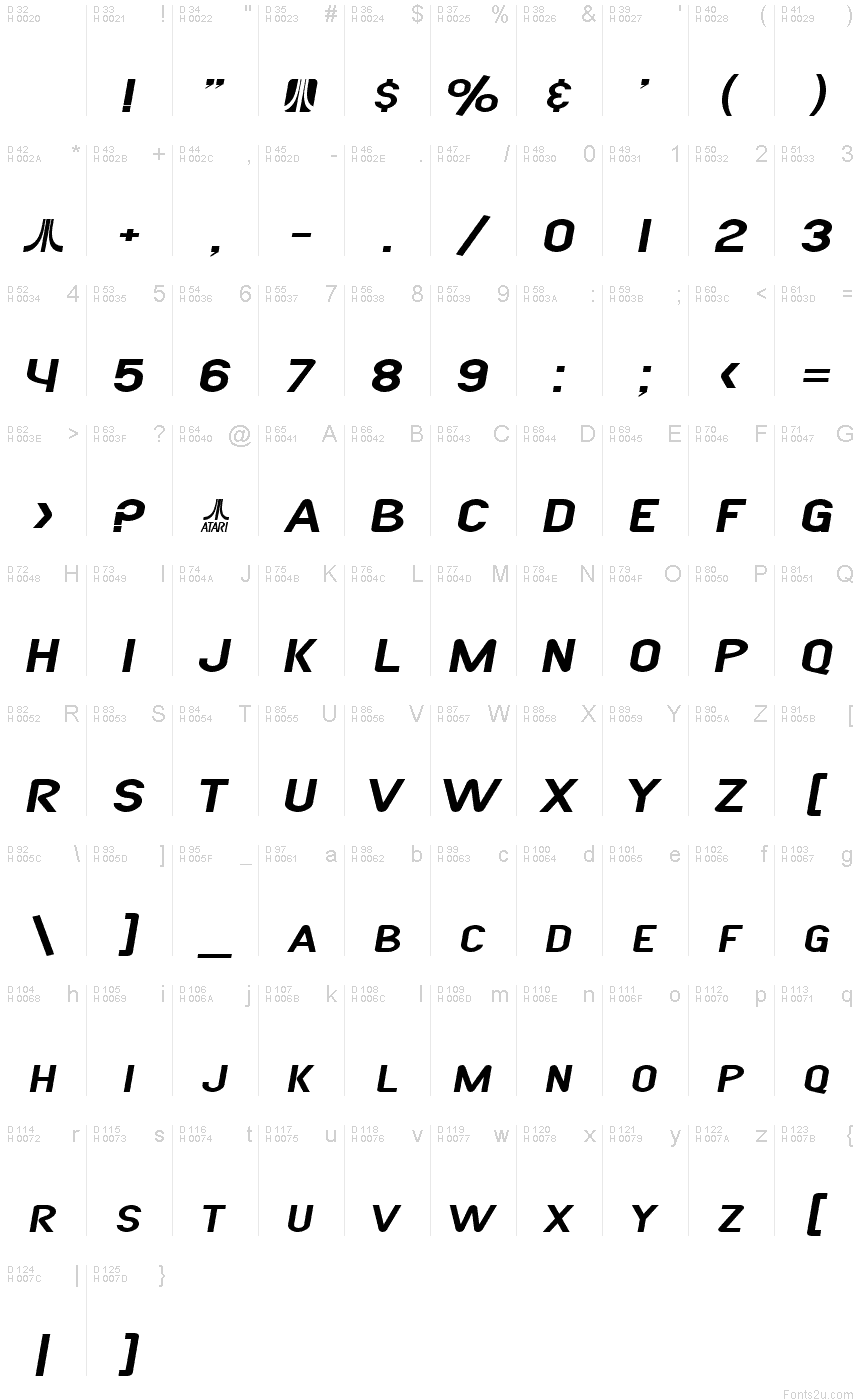
SF Atarian System Extended Italic od ShyFoundry to darmowy, retro-arkadowy bezszeryfowy krój pisma o charakternym, pochyłym zacięciu, przypominającym wczesne logotypy gier wideo. Litery są szerokie, mają ostre cięcia i konstrukcję opartą na wyrazistych, geometrycznych formach. Zestawienie ostrych skosów z masywnymi poziomymi kreskami nadaje fontowi dynamiczny, „ekranowy” rytm minionej ery.
Świetnie sprawdza się w plakatowych nagłówkach, opakowaniach w stylu sci-fi, na okładkach albumów, planszach tytułowych i w grafice gamingowej, gdzie rozciągnięta, kursywna dynamika potrafi utrzymać krótkie linie bez potrzeby stosowania dodatkowych efektów. Jako darmowy font, sprawdzi się również przy tworzeniu odznak, monogramów i szybkich projektów brandingowych, gdy zależy Ci na wyrazistym, cyfrowym klimacie lat 80. zamiast typowego, neutralnego bezszeryfu.
SF Atarian System Extended
ShyFoundry
Derek Vogelpohl